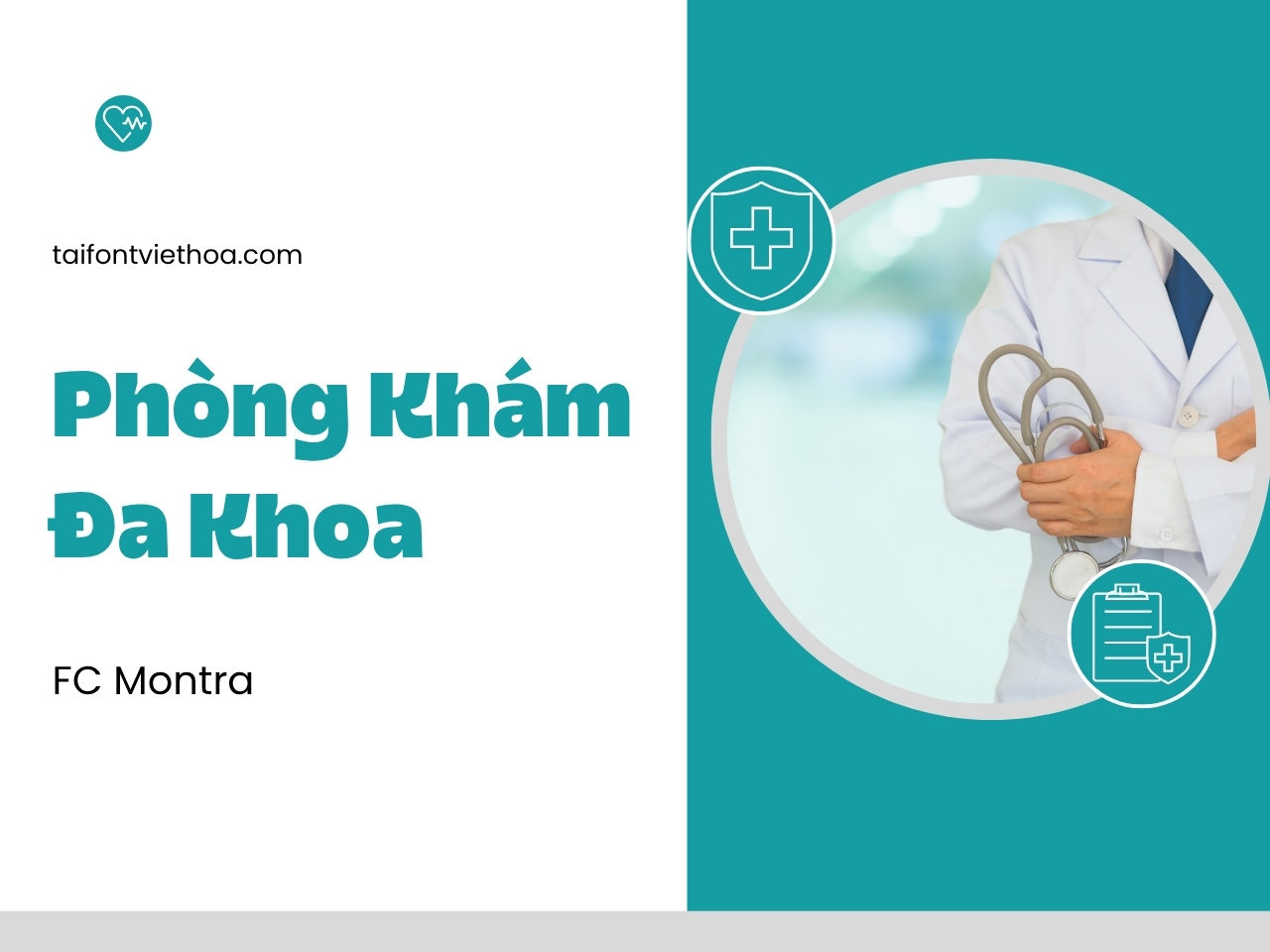
Giới thiệu về font Montra và phiên bản Việt hóa
FC Montra là một phiên bản Việt hóa độc lập từ font gốc “Montra” – một thiết kế sans-serif hiện đại thuộc Surplus Type Co., nổi bật với cấu trúc geometric tối giản, mang đến cảm giác chuyên nghiệp và dễ tiếp cận. Được phát hành chính thức trong những năm gần đây, Montra đã nhanh chóng trở thành lựa chọn ưu tiên trong thiết kế nhận diện thương hiệu, giao diện người dùng (UI/UX) và các sản phẩm truyền thông đòi hỏi sự rõ ràng, tối ưu.
Khác với bản “1FTV VIP Montra”, phiên bản FC Montra do cộng đồng Font Chuẩn thực hiện có quá trình Việt hóa tỉ mỉ, đảm bảo độ tương thích cao với bảng mã Unicode và hỗ trợ đầy đủ tiếng Việt. Từng dấu và glyph đặc trưng được tinh chỉnh bằng tay để hài hòa hoàn hảo với tinh thần thiết kế nguyên bản. Font hiện đã được taifontviethoa.com tuyển chọn và chia sẻ, mang lại giải pháp font sans-serif chất lượng cho các nhà thiết kế cần một công cụ mạnh mẽ, hiện đại và chuẩn chỉnh cho môi trường số.
Đặc điểm thiết kế và khả năng ứng dụng của Montra
Montra sở hữu cấu trúc chữ geometric sans-serif, các ký tự được thiết kế cân đối, đường nét liền mạch và bo góc nhẹ nhàng. Độ dày ổn định giúp font luôn giữ được độ rõ ràng, dễ đọc ở cả kích thước nhỏ và lớn. Phần chữ in hoa trong Montra rất mạnh mẽ, phù hợp với các tiêu đề, trong khi chữ thường vẫn giữ được nét mềm mại và thân thiện cho nội dung dài.
Font này cực kỳ phù hợp với các thiết kế giao diện người dùng (UI/UX), ứng dụng web, app, các tài liệu thương hiệu hoặc bao bì hiện đại. FC Montra cũng là lựa chọn lý tưởng trong các lĩnh vực như công nghệ, truyền thông kỹ thuật số, quảng cáo, bất động sản cao cấp và tổ chức sự kiện.